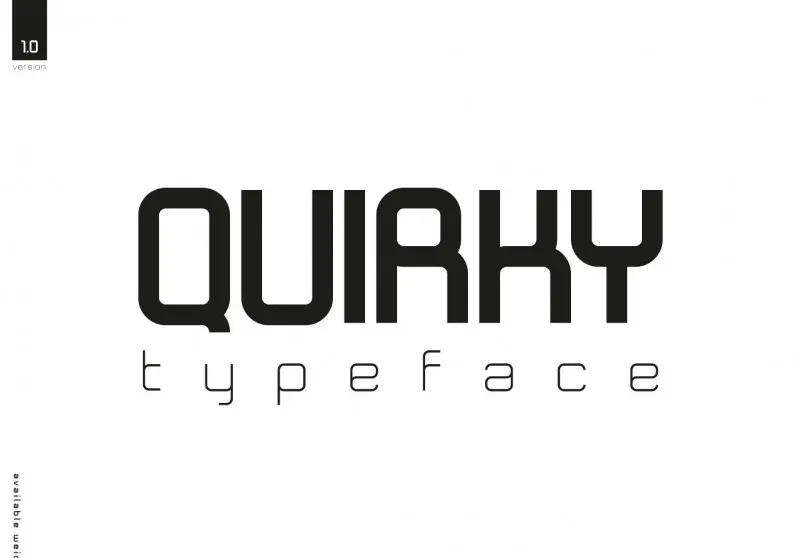
Quirky Font Family
Esta família de fontes sans-serif é a escolha perfeita para quem busca algo único e moderno que destaca-se no ambiente digital e impressos. A Quirky Font Family apresenta um ar elegante mas também distinto, combinando sofisticação com uma rara modernidade. Ideal tanto para criações visuais como logotipos e identidades de marca quanto para cartões de visita, material promocional e até mesmo decoração de festas, esta fonte é versátil e capaz de se adaptar a um vasto leque de formatos. Seja em uma impressão profissional ou em um post na rede social, ela garante um design arrojado e único que certamente impressionará seus convidados e seguidores. Nada melhor do que uma fonte que traz originalidade para deixar sua marca mais marcante no mundo digital. Não perca tempo, junte-se a essa família exclusiva e personalize seu próximo projeto de design com o charme da Quirky Font Family.